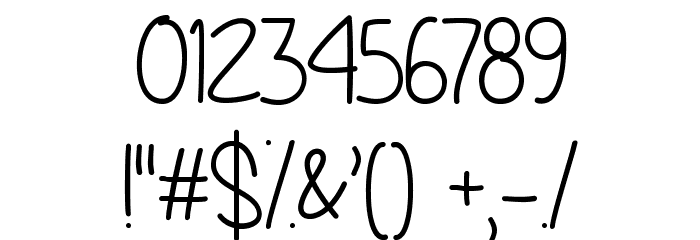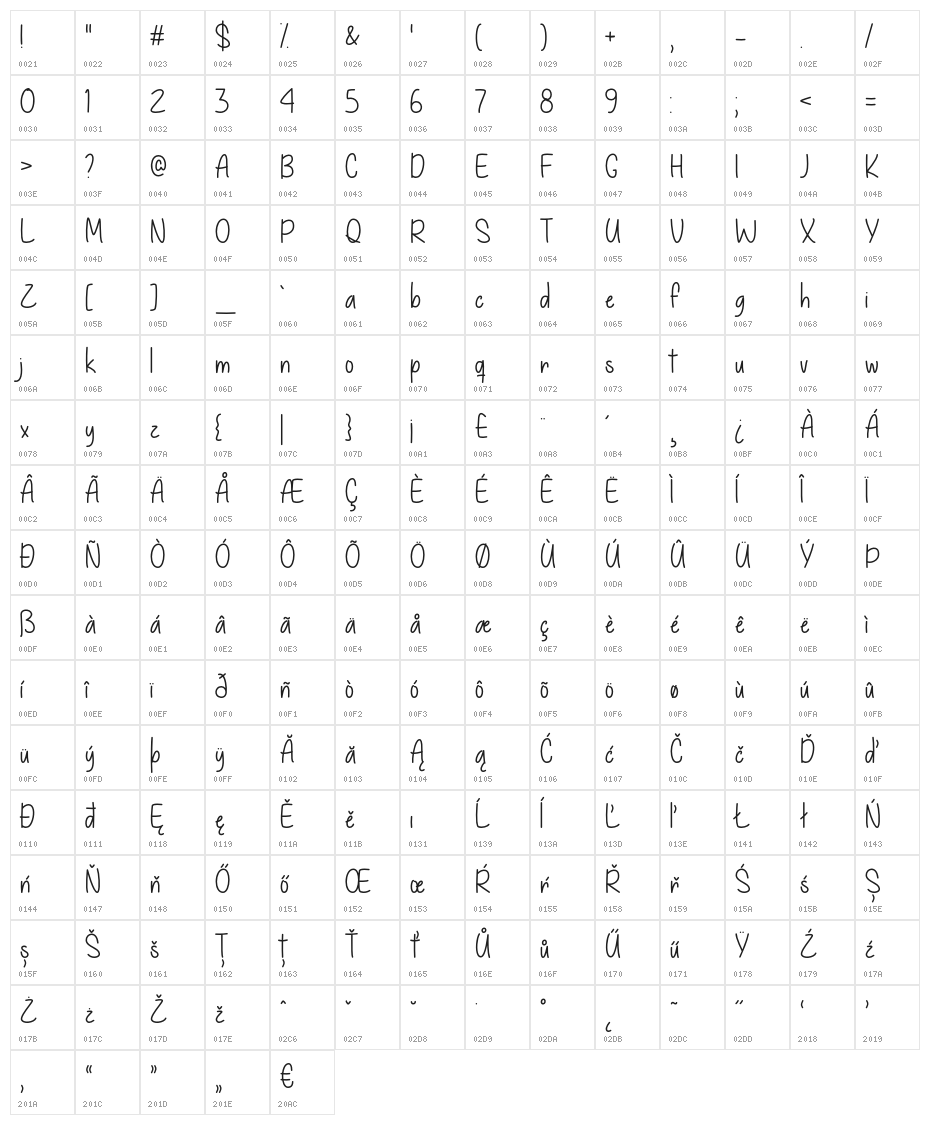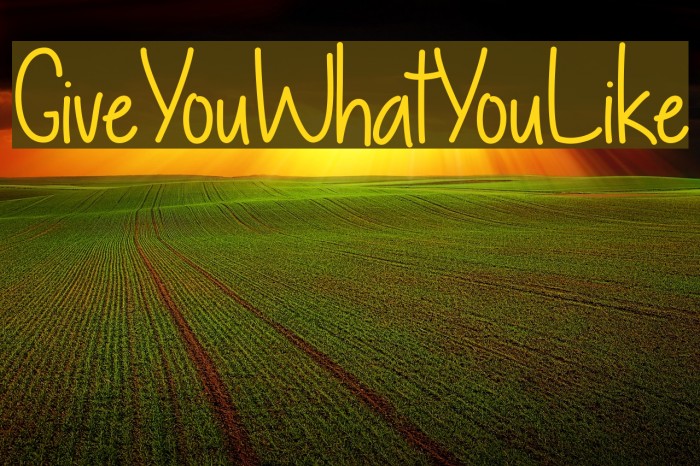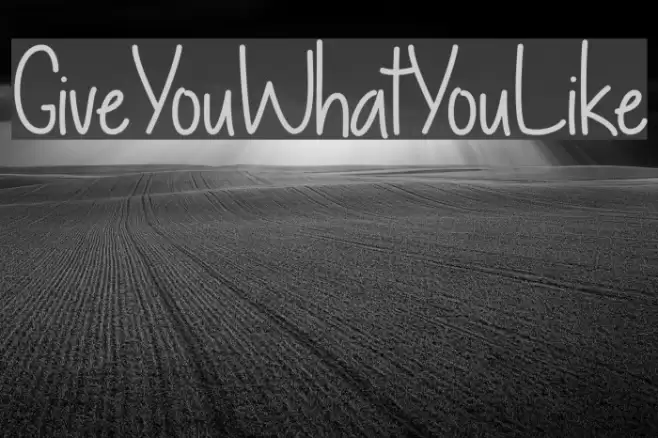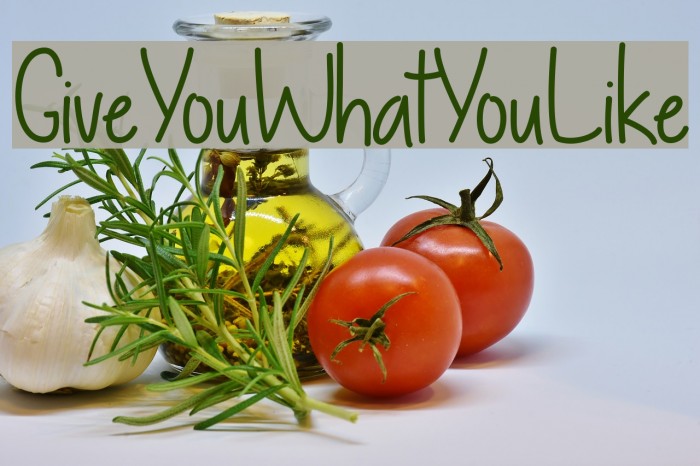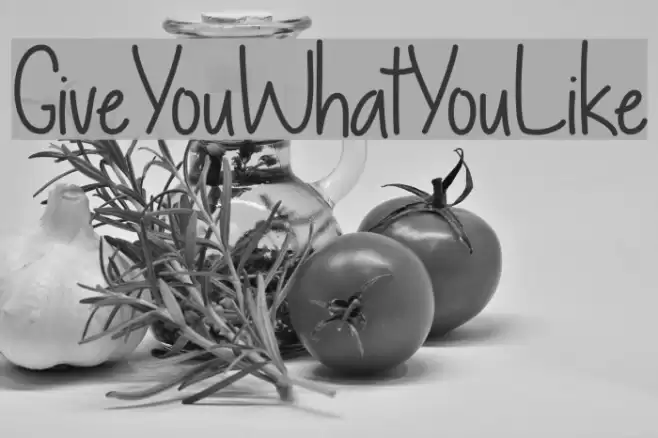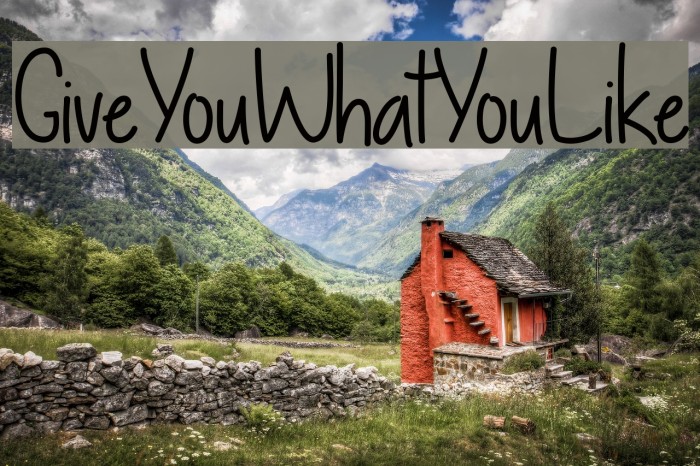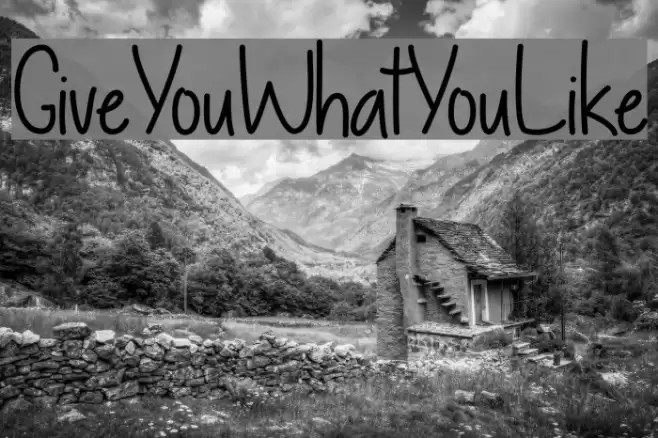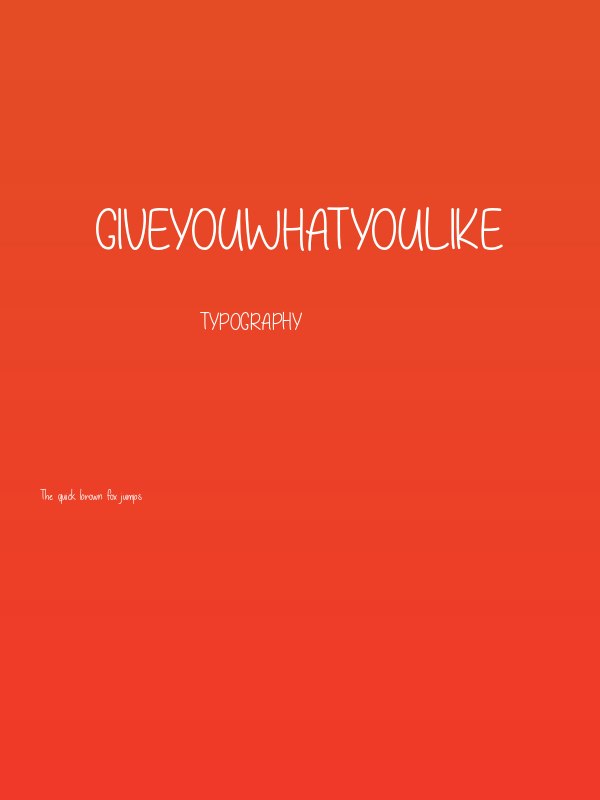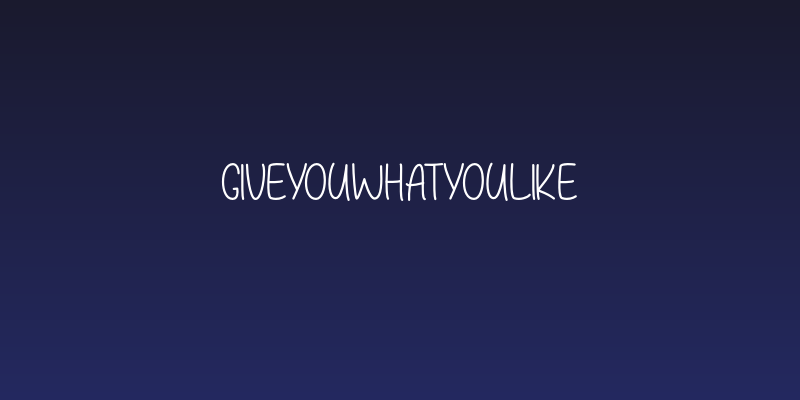
GiveYouWhatYouLike Font
| Gesamtstil | Casual |
| Anwendungsfall | Headlines, Logos, Informal text |
| Vorgeschlagene Projekte | Ideal for greeting cards, personal invitations, children's books, and playful branding. |